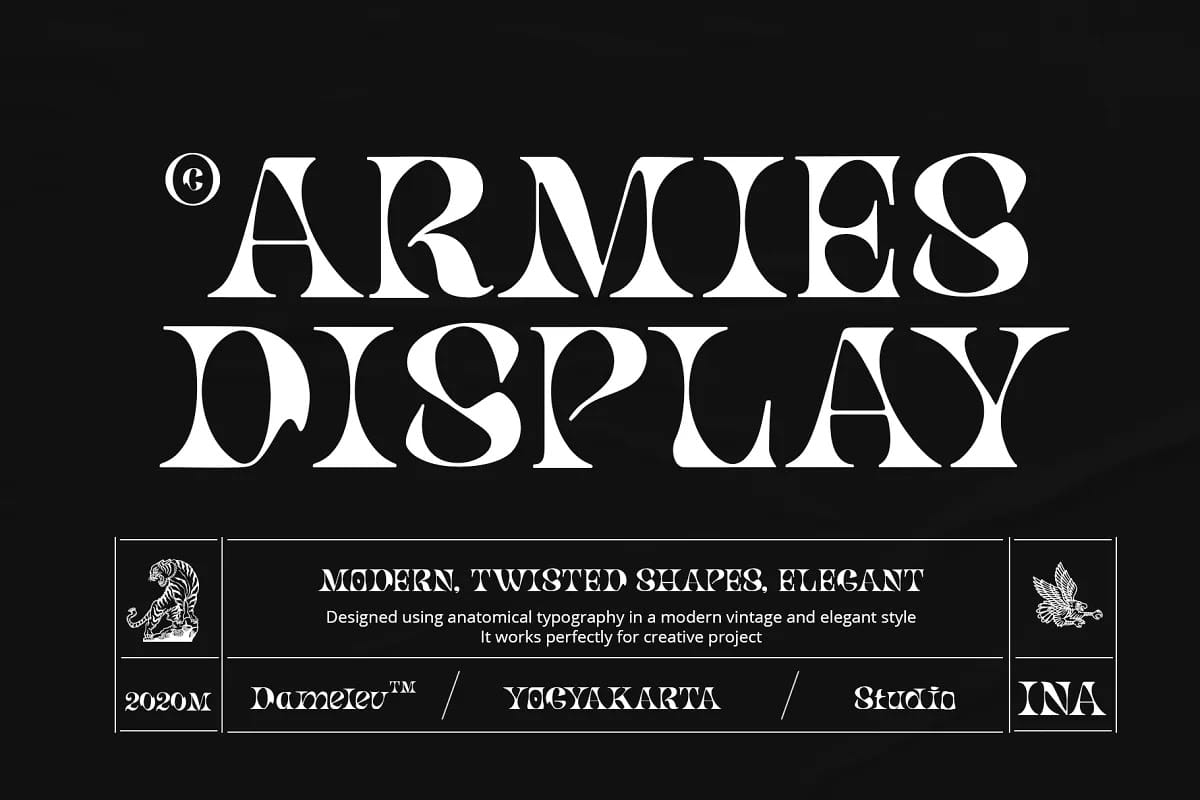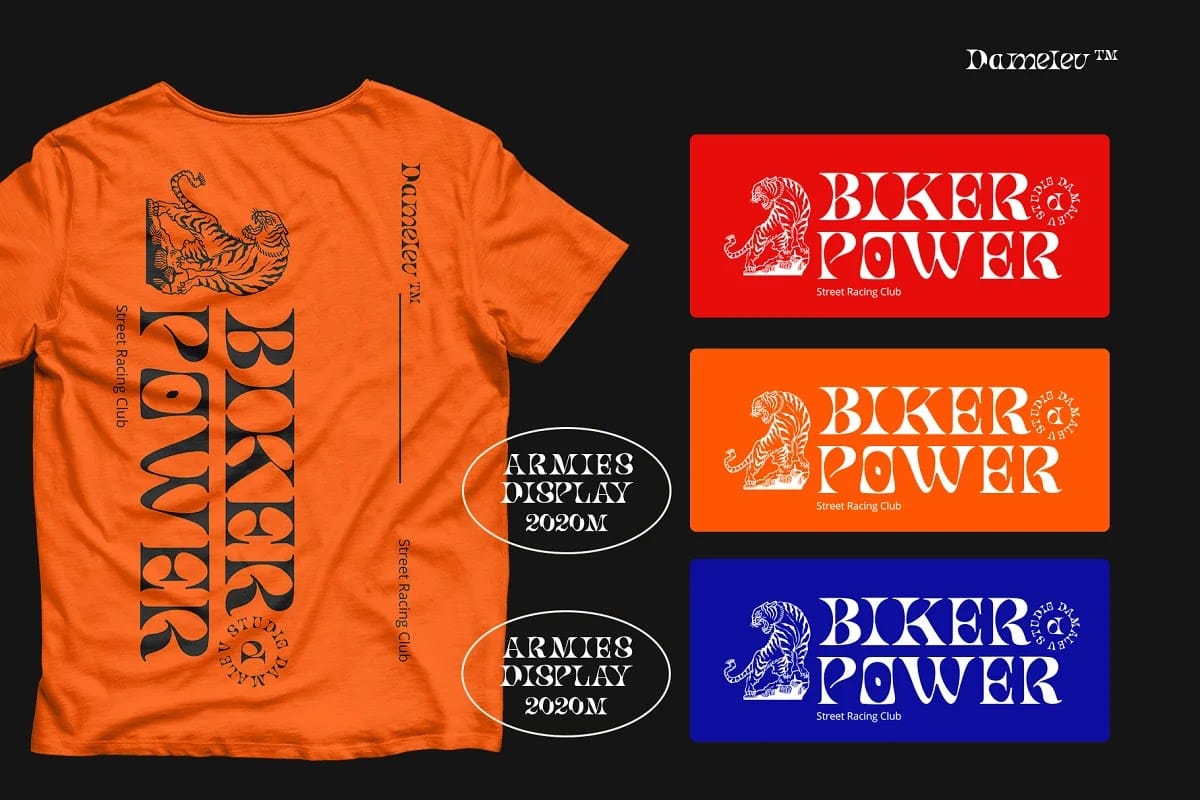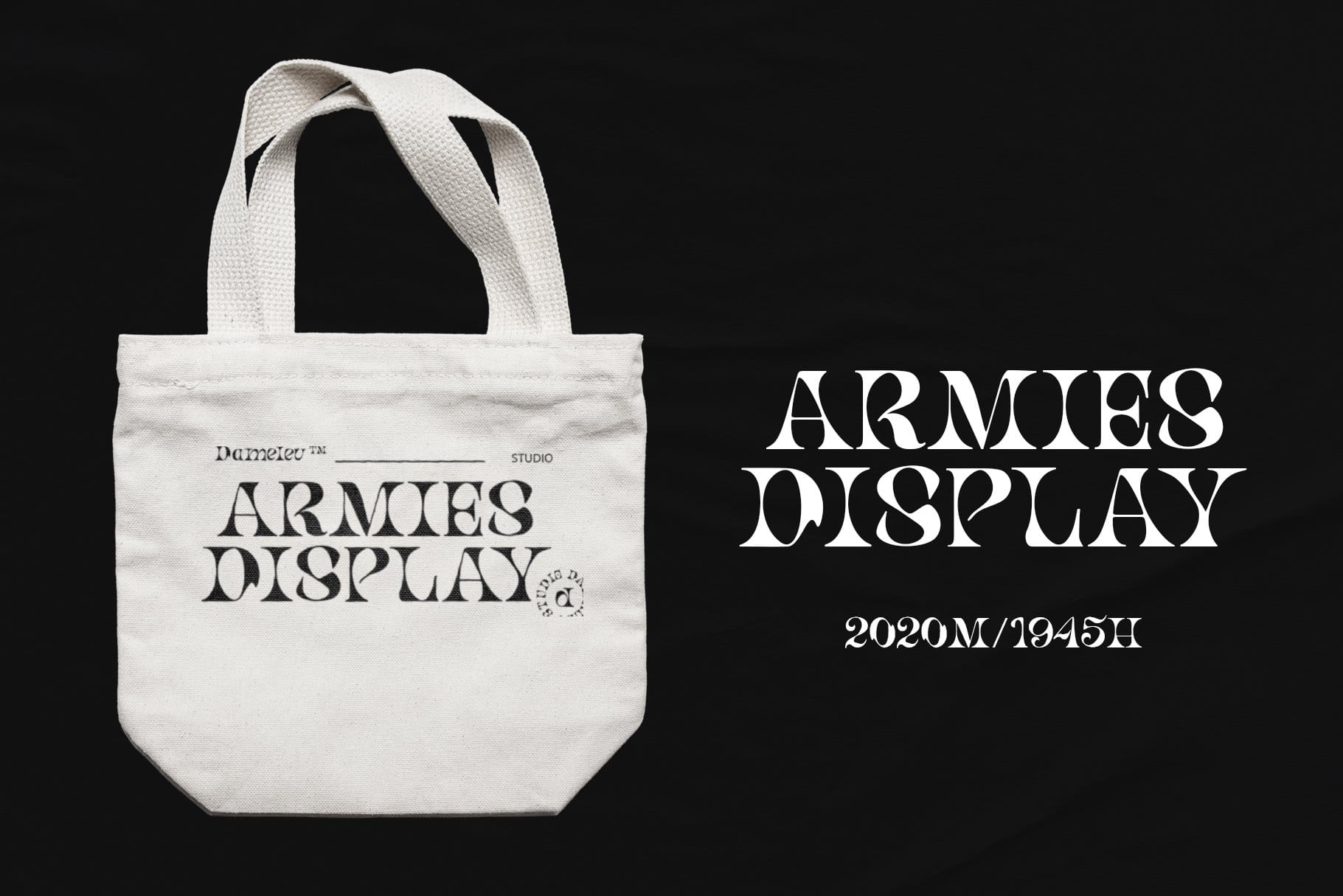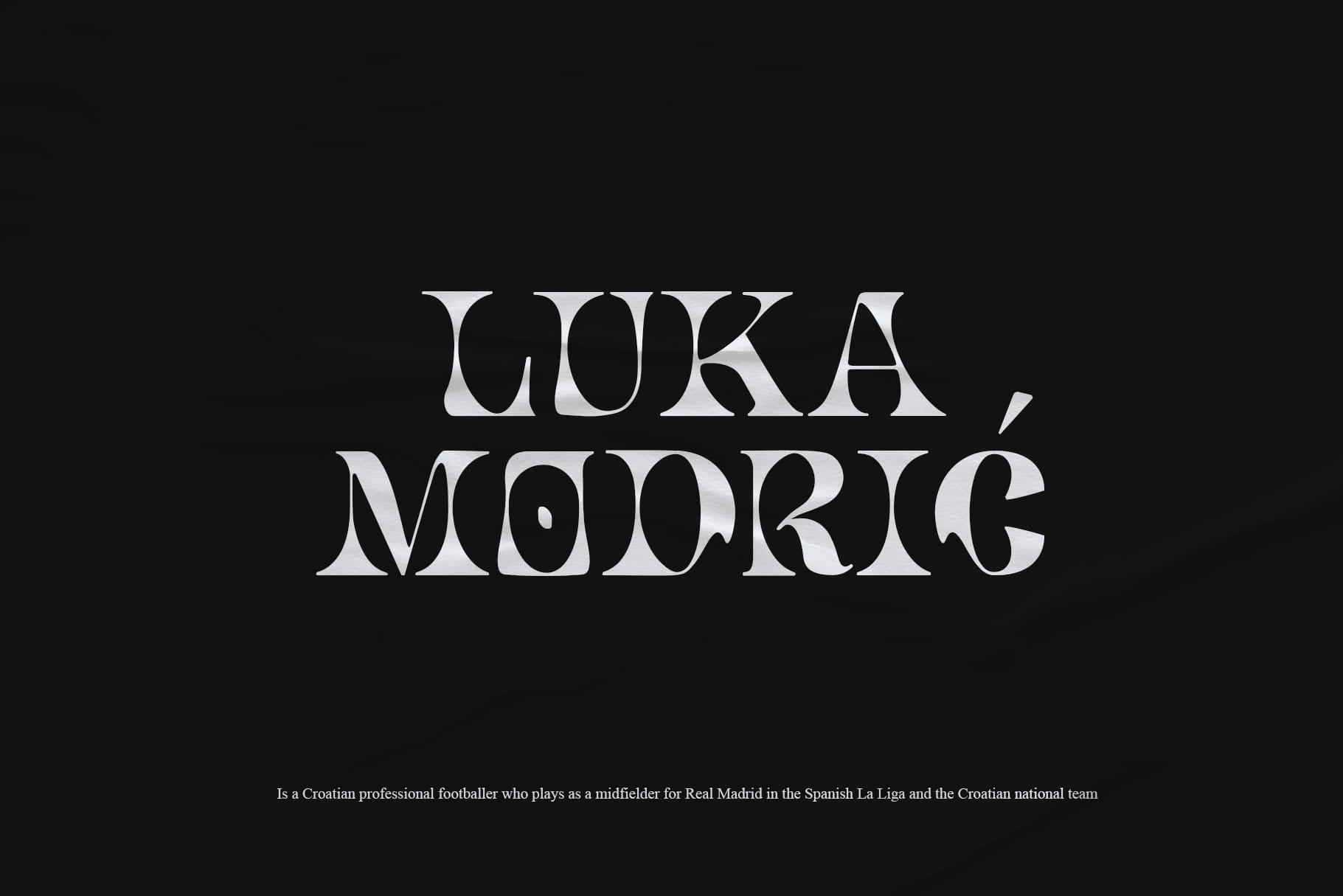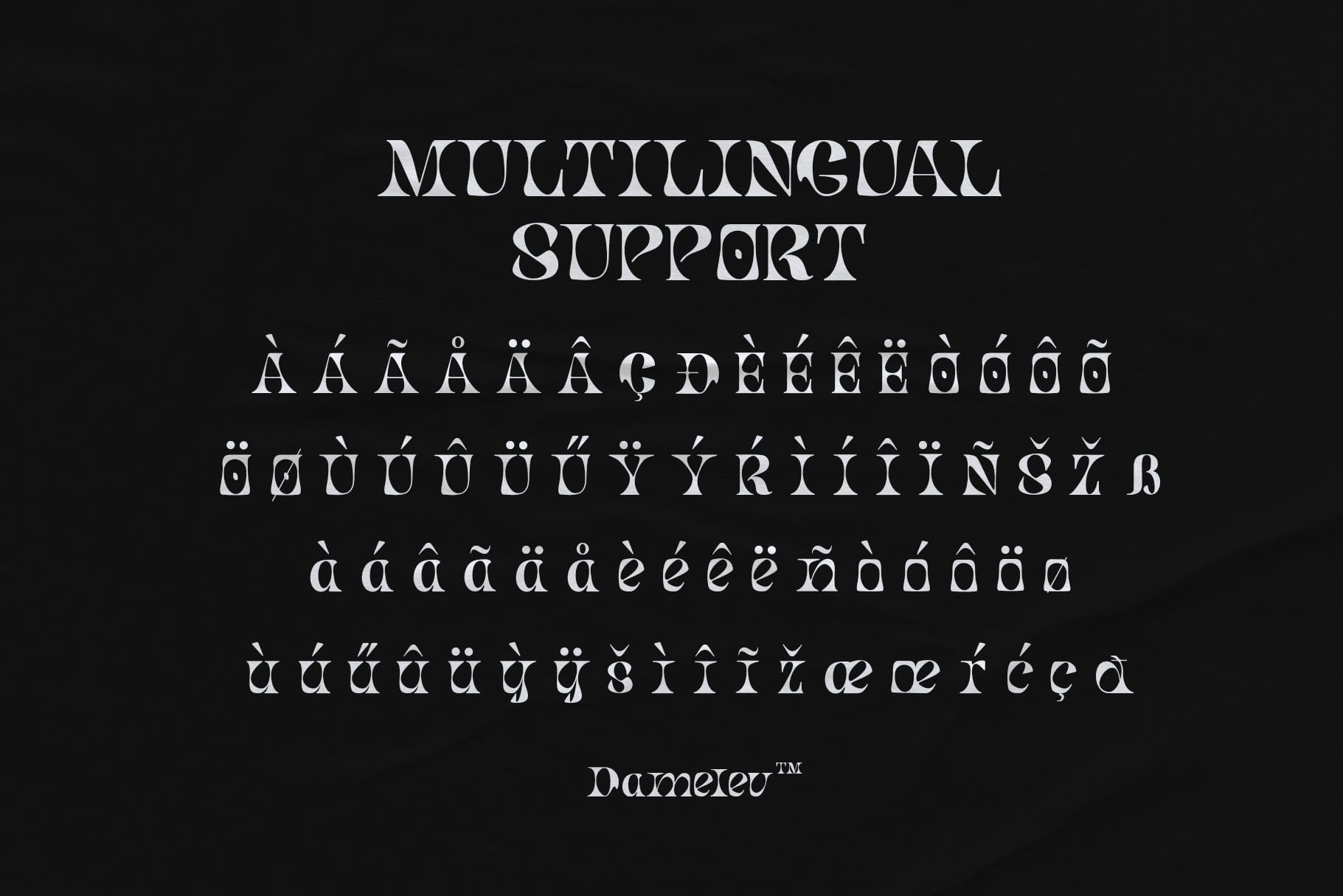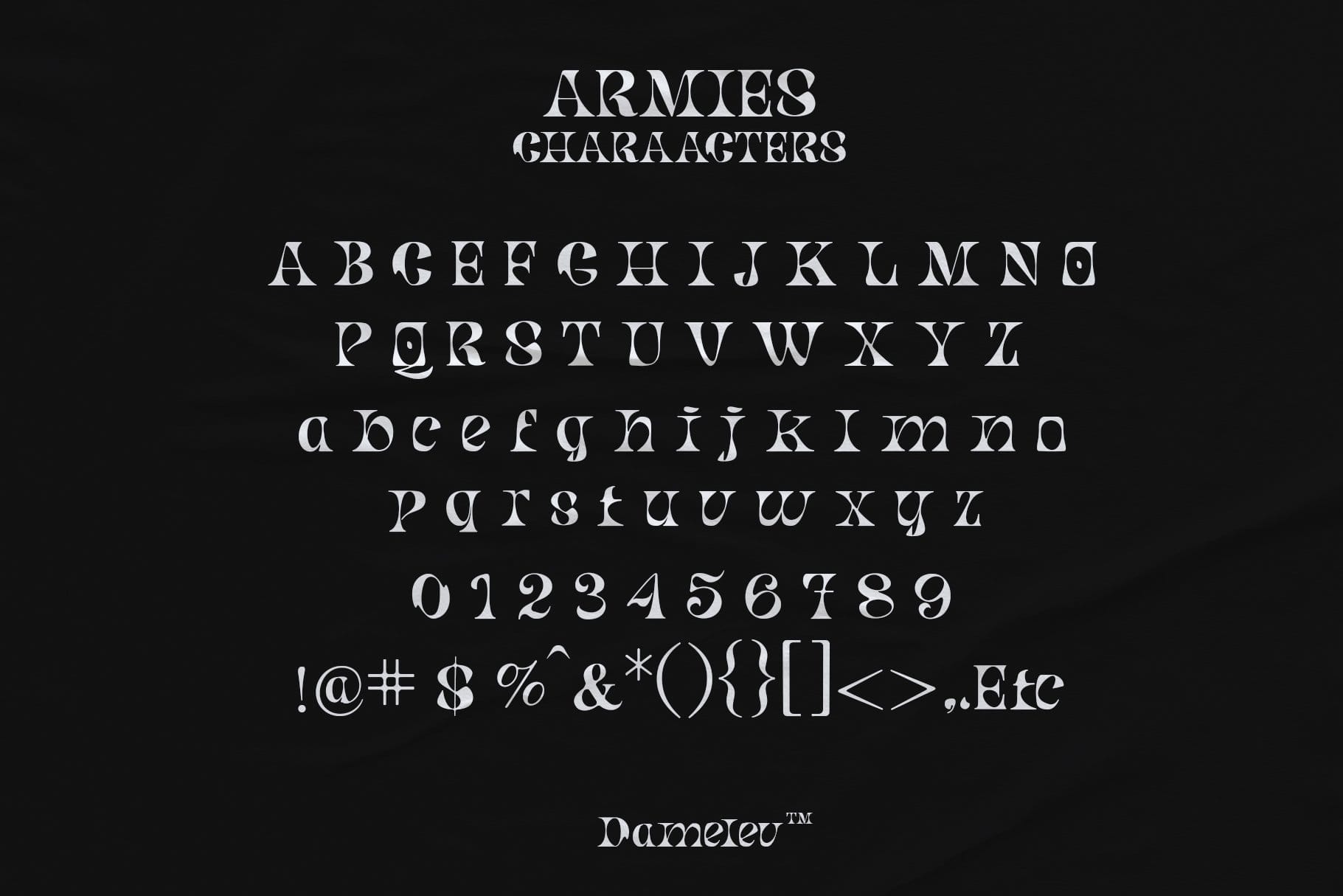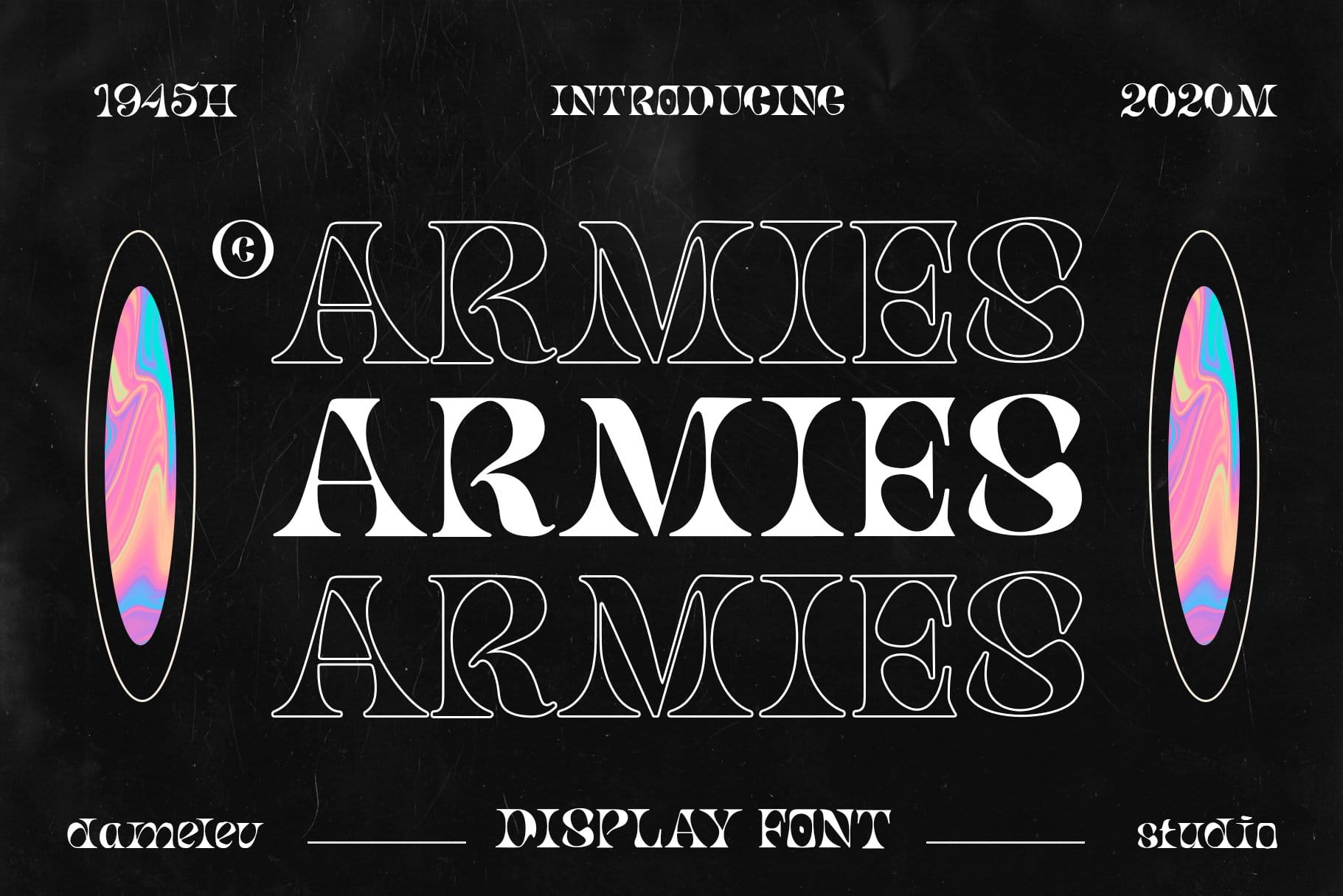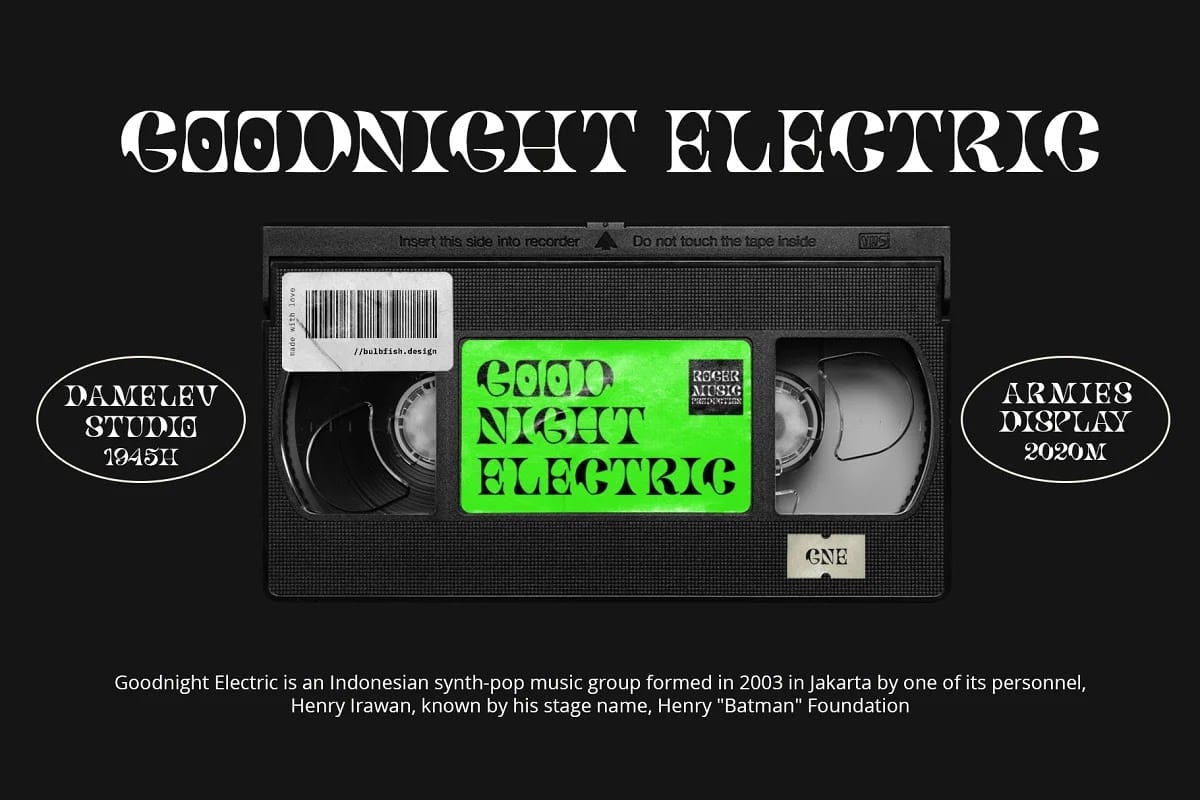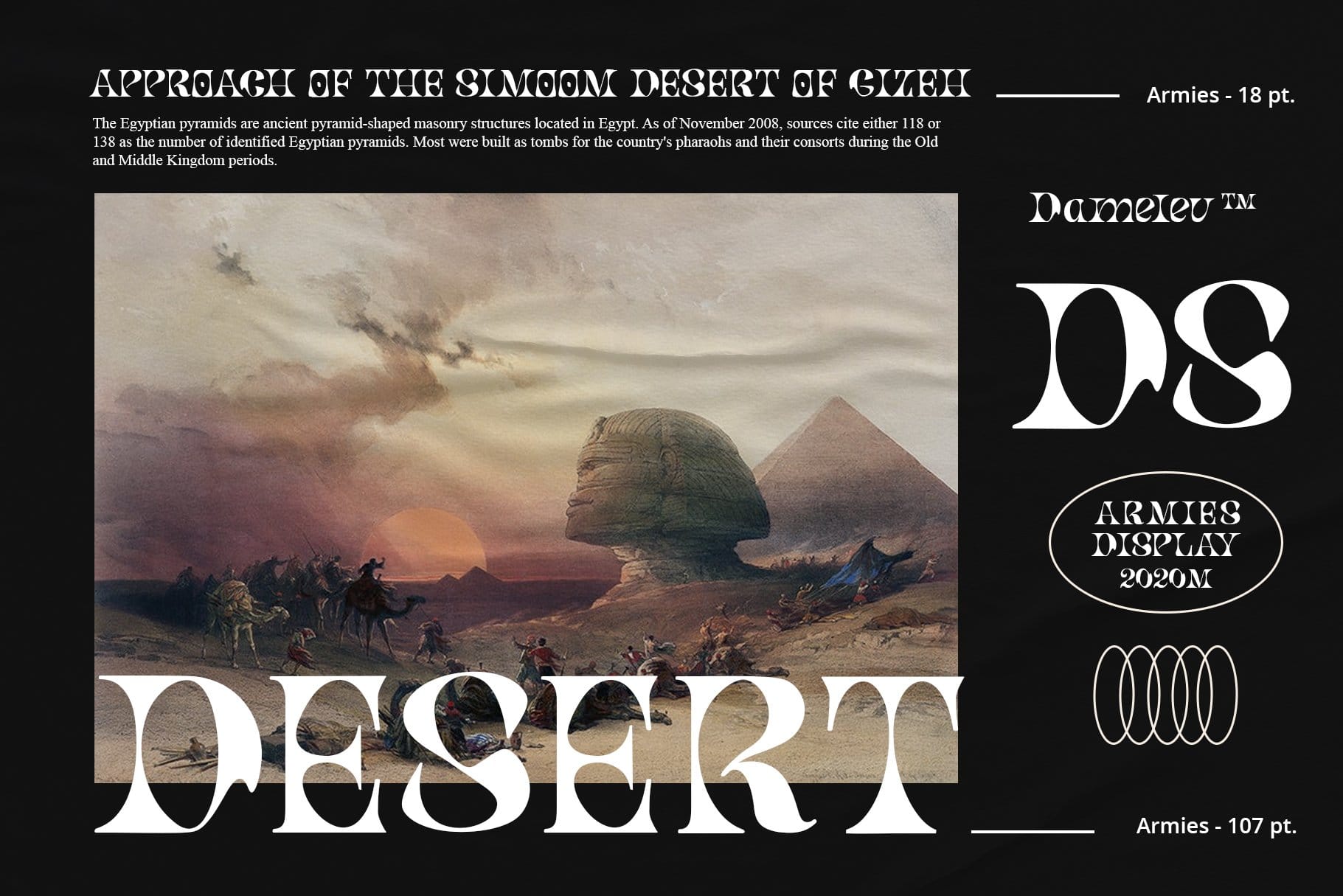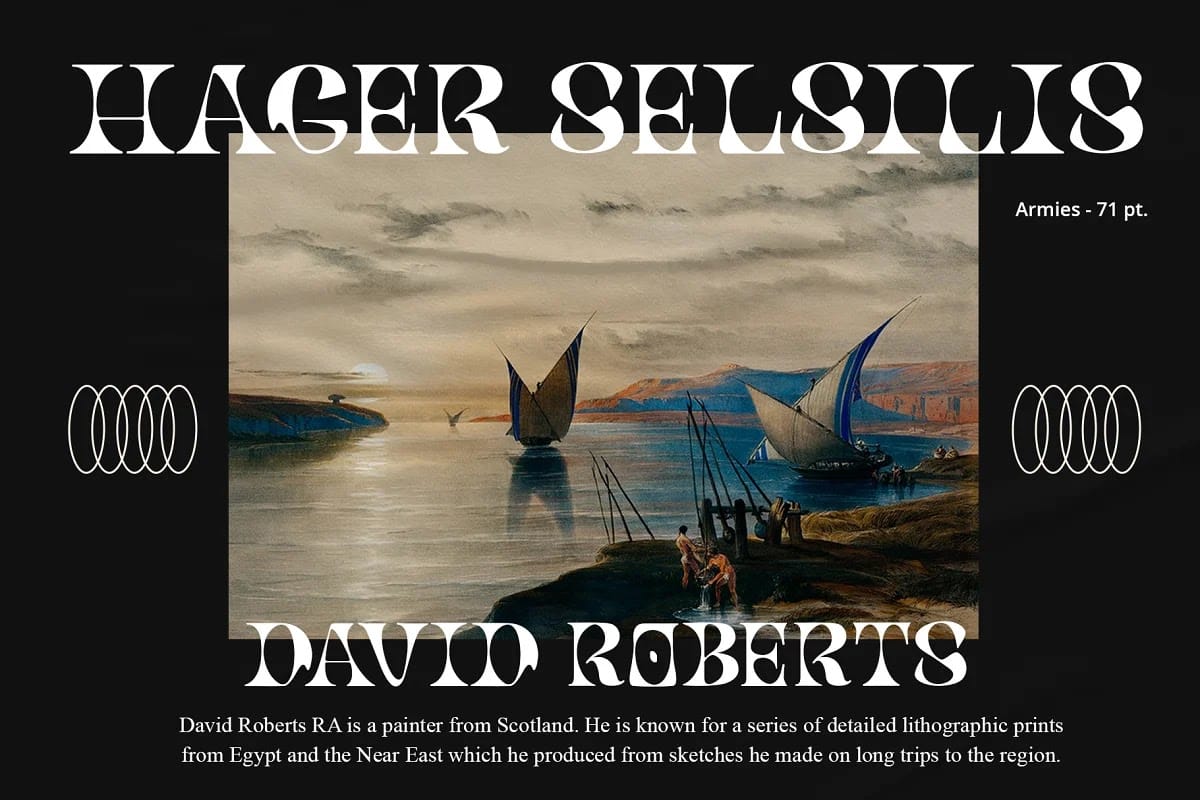
Font Armies Display – Font hiển thị độc đáo
Font Armies Display thuộc loại “hình xoắn” vì nó có các nét đậm. Nó cũng là một thiết kế có độ tương phản cao. Mặc dù nó có thể đọc được ở kích thước trung bình nhưng nó sẽ thực sự tỏa sáng nhất khi được sử dụng lớn như dùng cho tiêu đề.Nó hoạt động hoàn hảo cho các dự án sáng tạo như logo, áo phông / quần áo, huy hiệu, lời mời, bao bì, tiêu đề, áp phích, tạp chí, thiệp chúc mừng và lời mời đám cưới. Bạn có thể truy cập các tính năng open type và đa ngôn ngữ trên hầu hết các chương trình Adobe, chẳng hạn như Adobe Indesign, Adobe Illustrator, Adobe Photoshop…